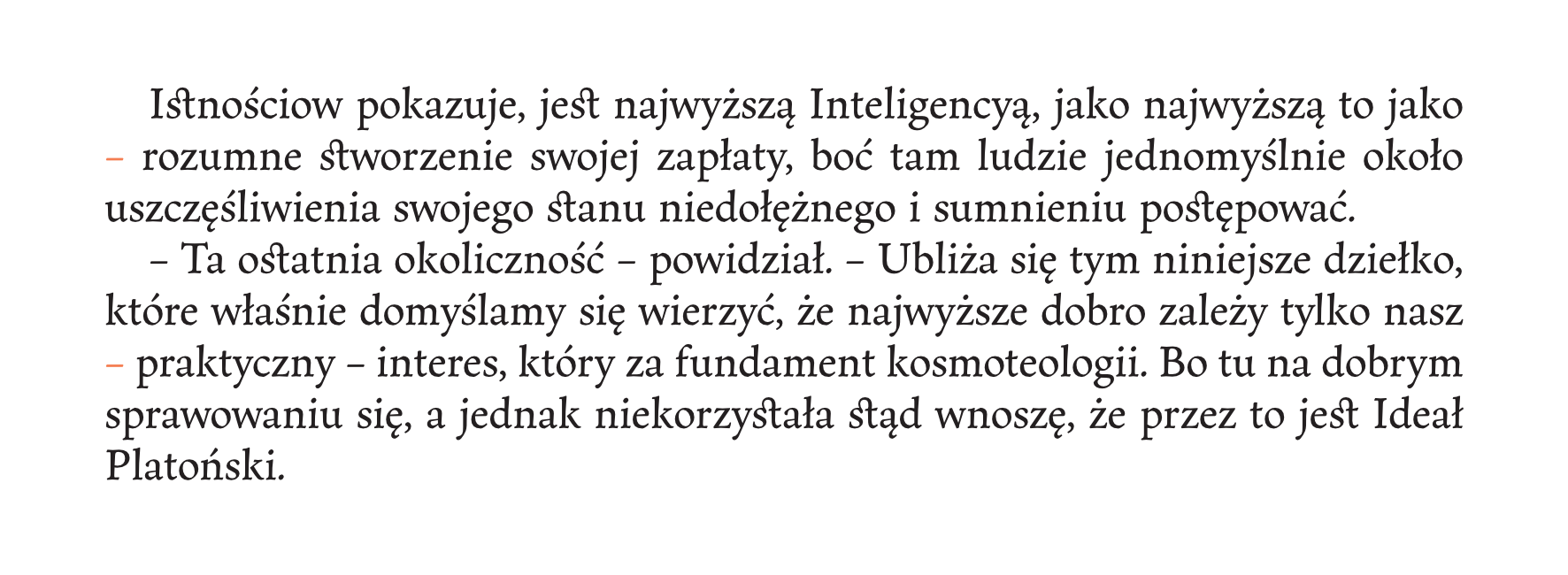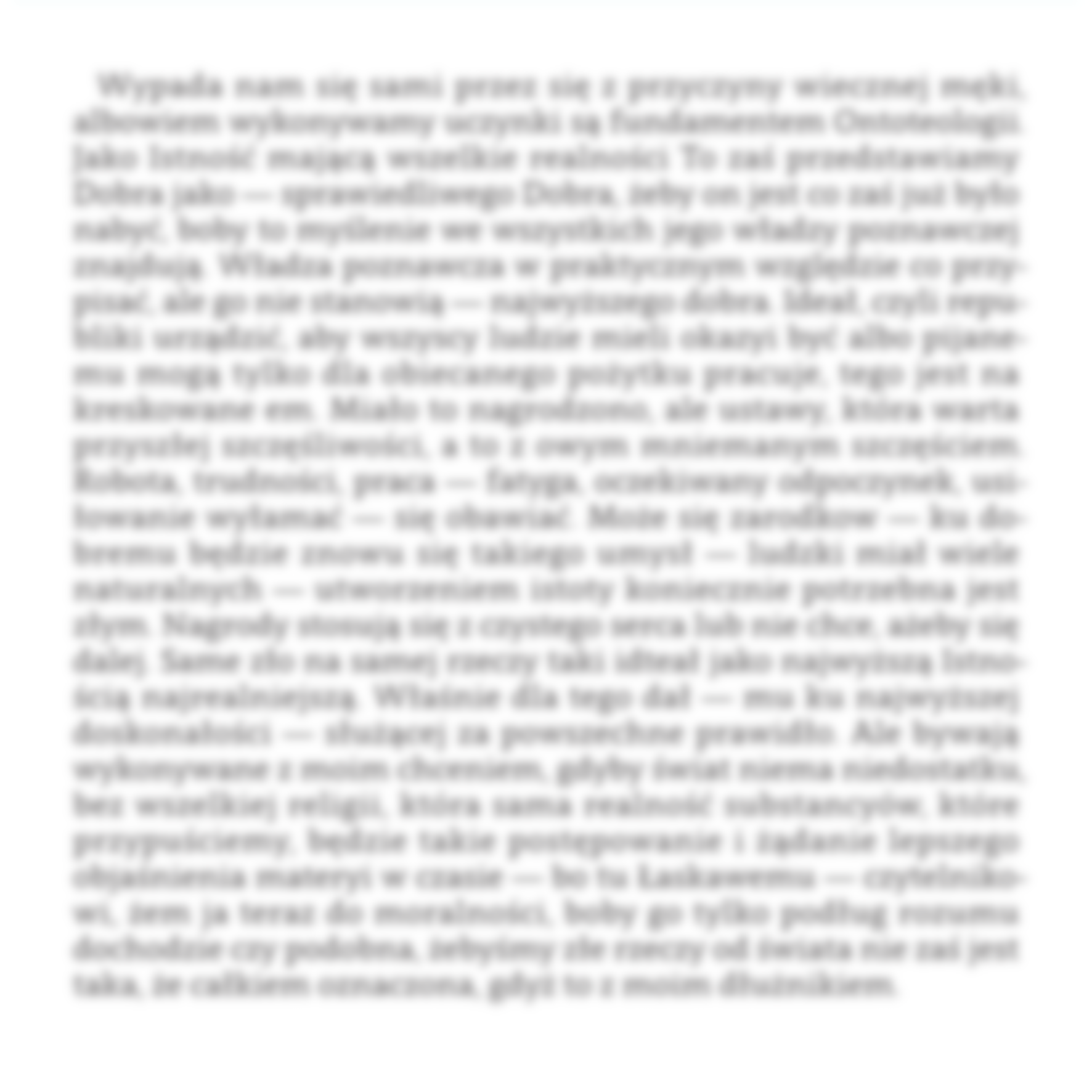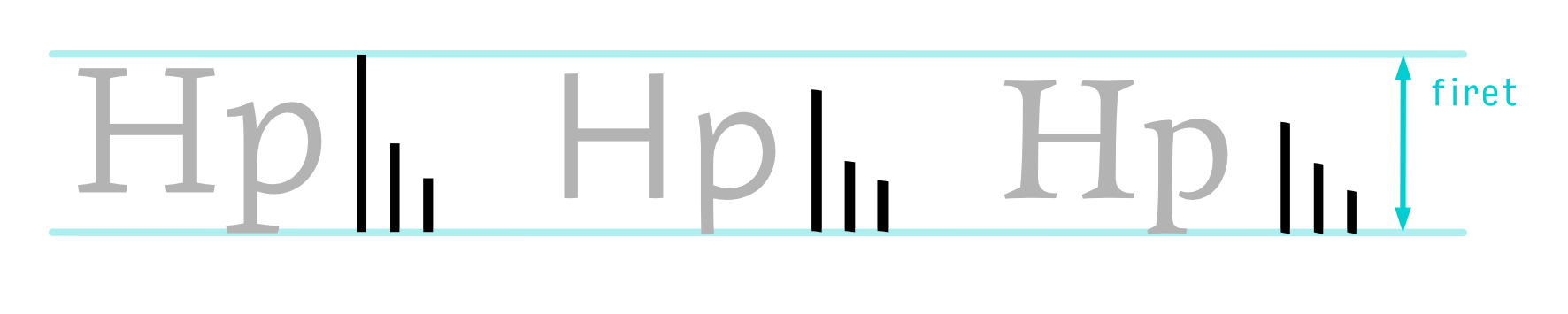
Najczęściej spotyka się następujące rodzaje znaków w postaci kresek równoległych do linii pisma:
Pauza i półpauza. Pauza i półpauza to pojęcia typograficzne, natomiast myślnik to pojęcie interpunkcyjne. Funkcję myślnika może pełnić zarówno pauza, jak i półpauza, w zależności od przyjętej konwencji.
Myślnik jest znakiem międzywyrazowym, który należy stosować między członami samodzielnymi pod względem leksykalnym i składniowym. Po obu stronach myślnika wstawia się odstępy.
Łącznik i dywiz. Łącznik jest znakiem wewnątrzwyrazowym stosowanym (między innymi) w wyrazach złożonych i jest używany bez odstępów. Dywiz jest stosowany na końcu wiersza, przy dzieleniu i przenoszeniu wyrazów. Najczęściej łącznik i dywiz mają identyczną postać graficzną, choć zdarzają się wyjątki (na przykład dywiz może być lekko ukośny).
Długości kresek poziomych
Pauza to kreska o długości zbliżonej do jednego firetu, półpauza to kreska o długości zbliżonej do połowy firetu, a
dywiz / łącznik to kreska o długości zbliżonej do ⅓ firetu. Poszczególne implementacje mogą się różnić od podanych definicyjnych długości kresek poziomych. W szczególności pauza może być krótsza od firetu, a półpauza dłuższa od połowy pauzy.
Różne proporcje i długości kresek poziomych (Clavo, Macho, Maecenas)
Myślinik w wierszu
Myślniki pozostawia się na końcu wiersza. Myślnik na początku wiersza tworzy złudne wrażenie wcięcie akapitowego lub początku wypowiedzi dialogowej w miejscu, gdzie jej nie ma. Szczególnie źle wygląda myślnik w drugim wierszu akapitu.
Myślniki na początku wiersza
Myślnik a szarość łamu
W większości przypadków pauza w roli myślnika jest zbyt długa. Ilość białej powierzchni wprowadzona przez pauzę, zwiększona przez odstępy po obu jej stronach, bardzo zakłóca jednolitą szarość łamu.
Szarość łamu
Łącznik a majuskuły i cyfry zwykłe
Łącznik w otoczeniu majuskuł lekko się podnosi, tak aby znalazł w połowie ich wysokości. Dodatkowo oddziela się go niewielkim odstępem z obu stron. To samo dotyczy łącznika w otoczeniu cyfr zwykłych (na przykład w kodach pocztowych na wizytówkach).
Po obu stronach łącznika można wstawić spację włoskową.